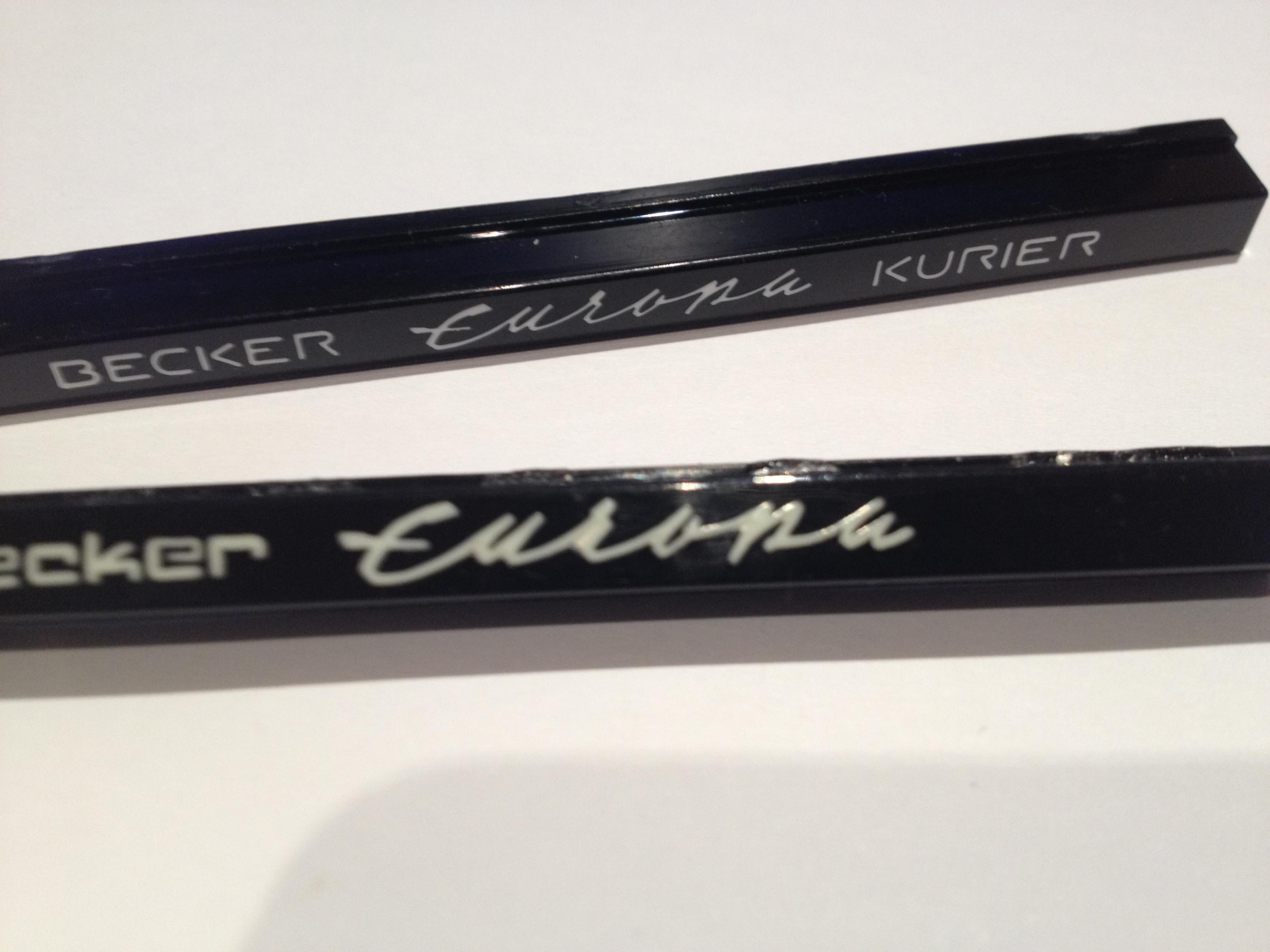
Schrift für Radioblenden Oldtimer
ich hatte schon mal nach dem Schriftzug "Europa" gefragt. Das hat sich erledigt, da die Schrift gezeichnet ist.
Hätte jetzt noch jemand eine Idee für die Schrift "Becker bzw. Kurier" ?
ich sehe da zwei verschiedene »Becker«-Fonts
den alten muss man wohl irgendwie nachbaun – die neuere Schrift bekommt man evtl. irgendwo aus dem Netz.
Wenn man nur ein Wort braucht bzw. Logo braucht man nicht unbedingt gleich den Font – oft ist in Logos ein bestehender Font auch umgearbeitet dass es einfacher ist gleich das Logo zu suchen.
oder eben, gerade bei Oldtimer-Logos sauber in einem Vektorgrafikprogramm selbst zeichnen. Zumeist sind solche Logos in 10 minuten bis eibner chalben Stunde (dann aber schon was richtig kompliziertes) nur nach dem Bild nachgezeichnet, die Zeit zur Suche eines Fonts ist da in der regel das vielfache, undmussman dann sen Font ohnehin noch verändern, also linien glätten, verfetten, abrunden usw, bedeutet das oft deutlich mehr Arbeit als die Linien gleich zu zeichnen.